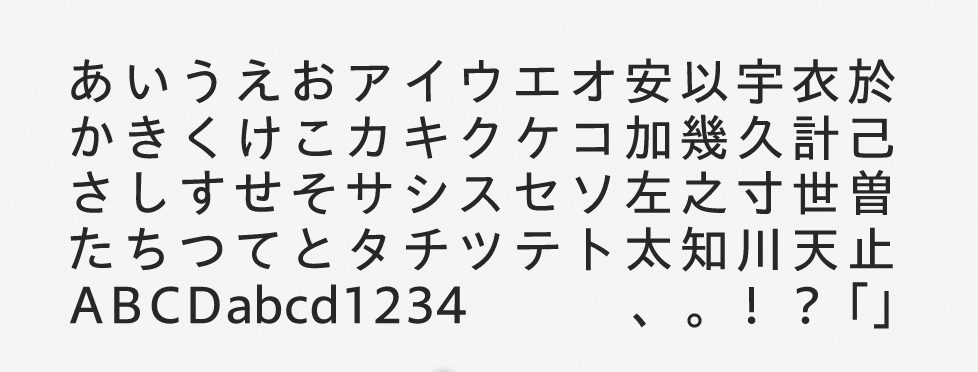
「あおとゴシック」について
あおとゴシックは、2021年の新書体として登場しました。デジタルデバイスの画面上に表示される本文用に開発されたフォントです。名称は、天然砥石の「青砥石」に由来しています。漢字はTBゴシックをベースに字面や一部の字形が調整されており、従属欧文は同時リリースの Sharoa Pro がベースとなりました。
「あおとゴシック」の特徴
本文に最適な書体で、ニュートラルなゴシック体であることが特徴です。長文も自然に読めるような癖のない素直な印象の骨格を採用しています。字面が小さめに設計されているため、長文を組んでも圧迫感を与えません。
デジタルデバイス向けらしく、横組みで違和感のないデザインであることも魅力です。基本的には本文向けですが、ELからDBまでの5段階のウエイトのほかに、小見出しなどで使えるBウエイトとEBウエイトも用意されています。
シンプルでスタイリッシュなので「本文向けでとても使いやすいな!」と感じます。シンプルでありながらも冷たい印象はなく、なだらかな曲線の影響で暖かみもありますね。今は画面表示に適した書体の需要も高く、これから多用されていきそうなフォントだと思います。